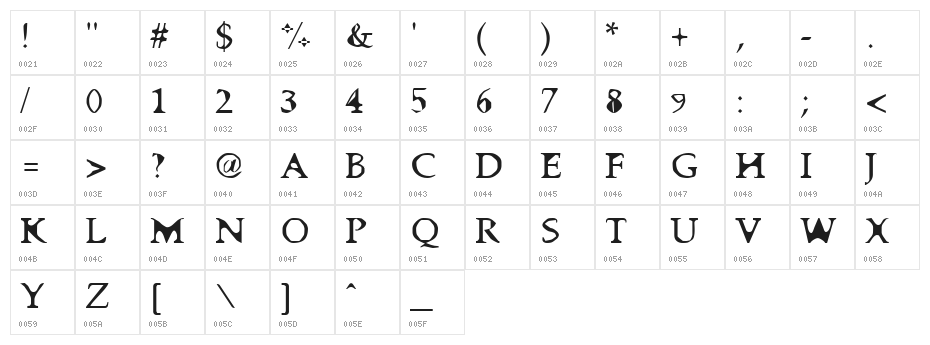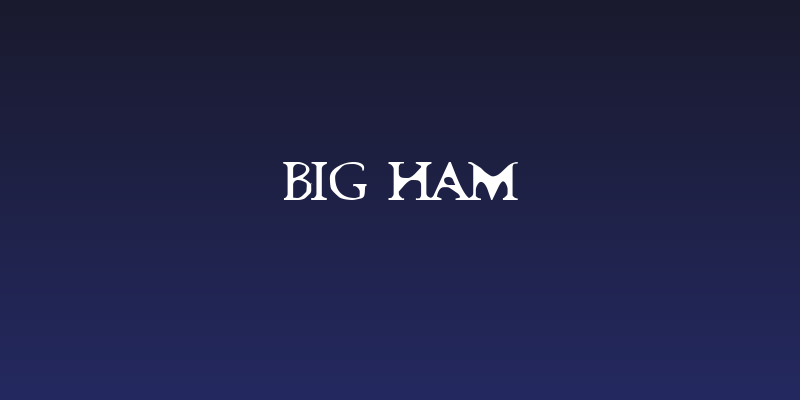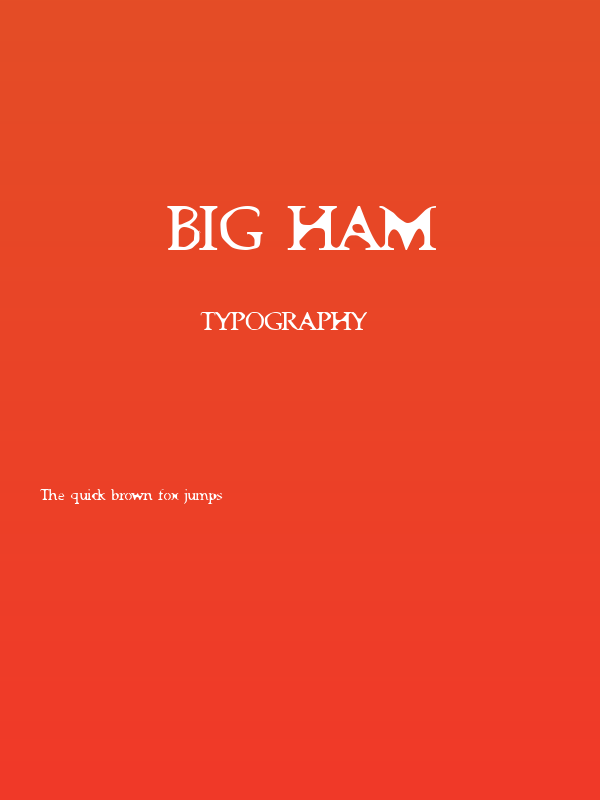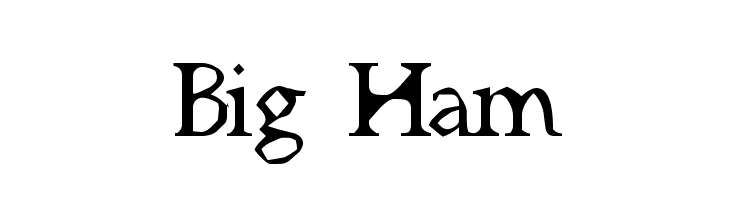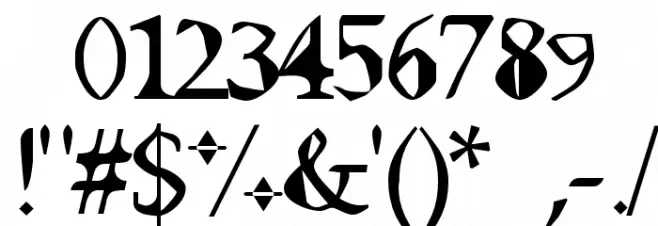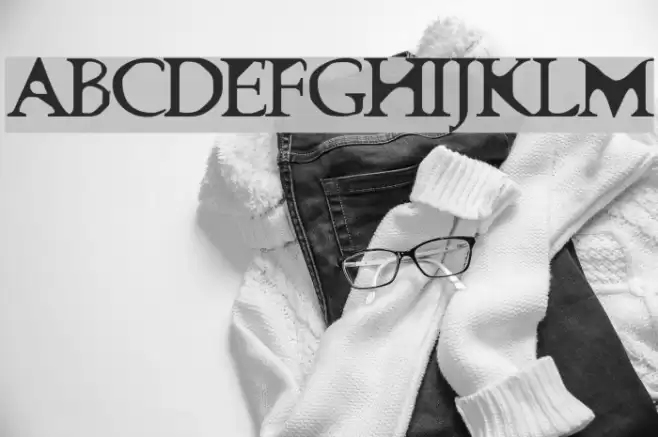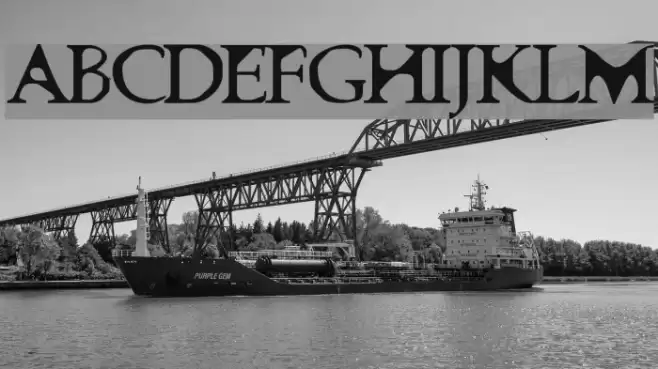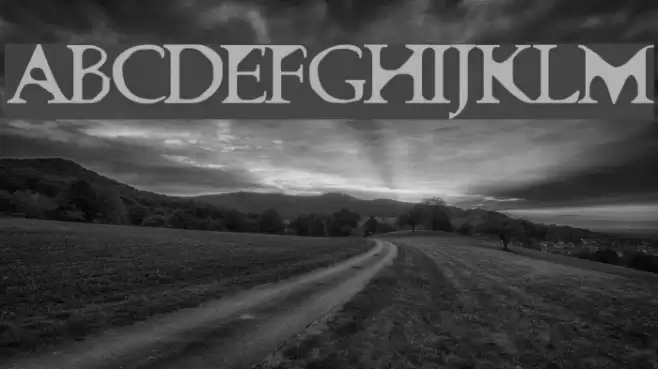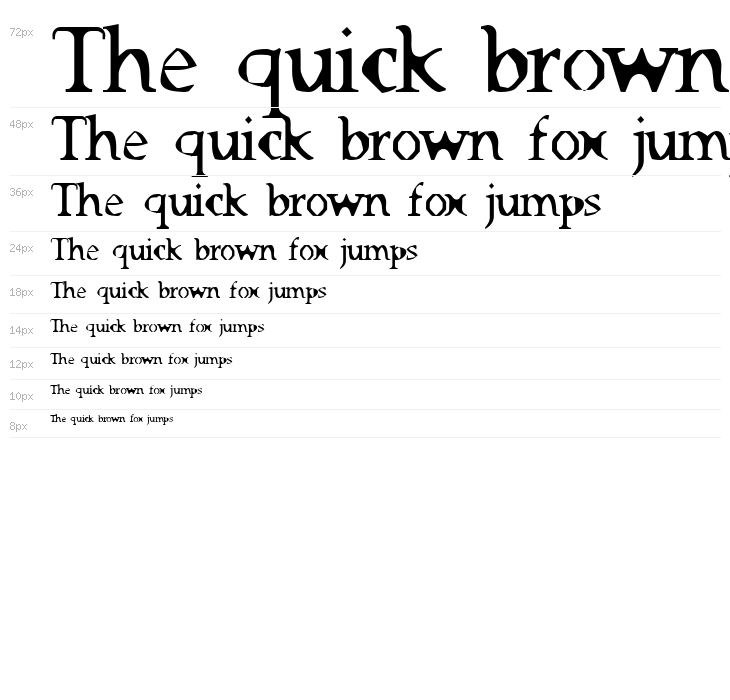
Big Ham Font
| Projetos propostos | Ideal for fantasy-themed designs, book covers, posters, and branding that requires a historical or dramatic touch. |